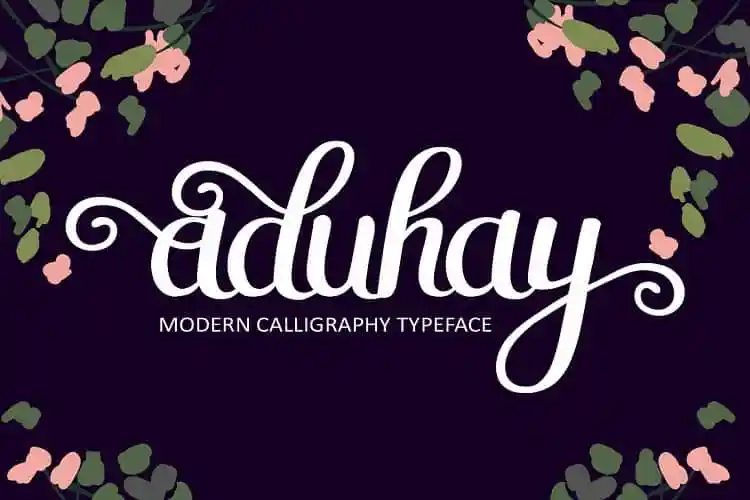
Aduhay Script Font – Download Grátis
Introduzimos Aduhay Script Font! Esta fonte premium foi criada por duasatu e pode ser encontrada na Creativemarket. Nesta descrição original em inglês, é mencionado que esta fonte, chamada Aduhay, tem um estilo personalizado. Ela é perfeita para criar cartões de convite (inicial), cabeçalhos, logotipos e até mesmo desenhar t-shirts ou roupas. Mas aqui está a descrição em português do Brasil que você solicitou: Introduzimos Aduhay Script Font! Esta fonte premium foi criada por duasatu e pode ser encontrada na Creativemarket. Nesta descrição original em inglês, é mencionado que esta fonte chamada Aduhay tem um estilo personalizado. Aduhay é uma tipografia a mão pintada com um toque único de arte handmade. Perfeita para criar cartões de convite (inicial), cabeçalhos, logotipos e até mesmo desenhar t-shirts ou roupas. Uma das características deste design é seu fluxo fluido, contando com o toque único de arte handmade característico.